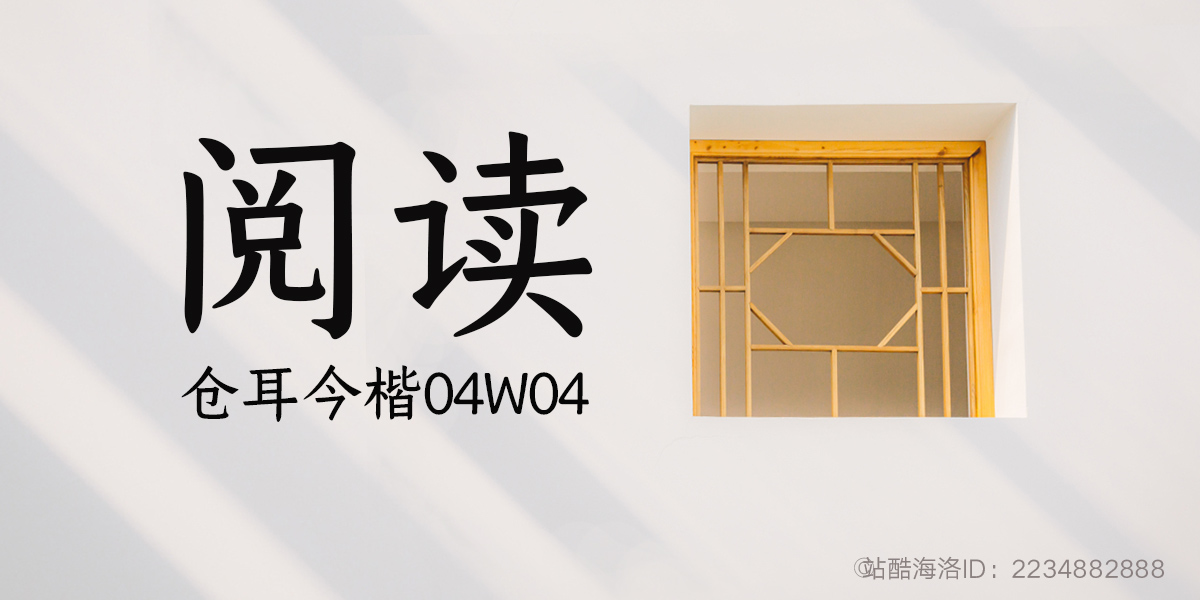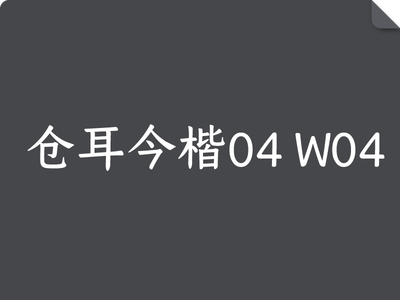
仓耳今楷04 W04
仓耳今楷04 W04,这套字体是包含2.7万字的大字库,是创新型的正文字体,在字体结构上借鉴了传统楷体的结构特点,在笔形上重新设计,吸收了中国传统书法的风韵,笔形的边缘弧线平滑过渡,字体更显端庄优美。字体在电子屏幕上的识别度高,使读者能够从中获得更为舒适、愉悦的阅读体验。
楷体